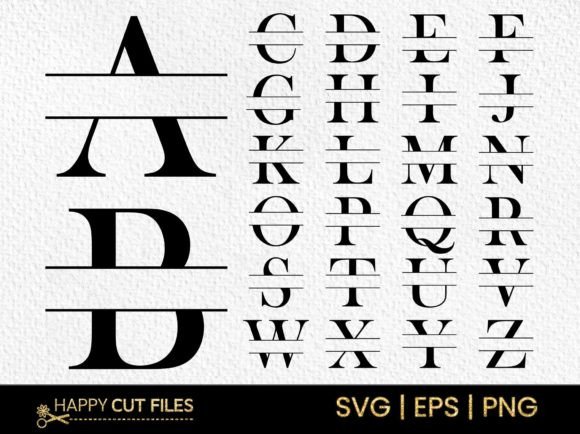
Split Letter Monogram SVG Font a-Z Png
Nếu bạn đang tìm kiếm các tài nguyên chất lượng cao như Split Letter Monogram SVG Font a-Z Png, gói cao cấp này là một lựa chọn tuyệt vời cho các dự án sáng tạo của bạn.
Được chế tác với độ chính xác cao, Split Letter Monogram SVG Font a-Z Png cung cấp các vector sạch, kiểu chữ mượt mà và giấy phép thương mại để bạn yên tâm.